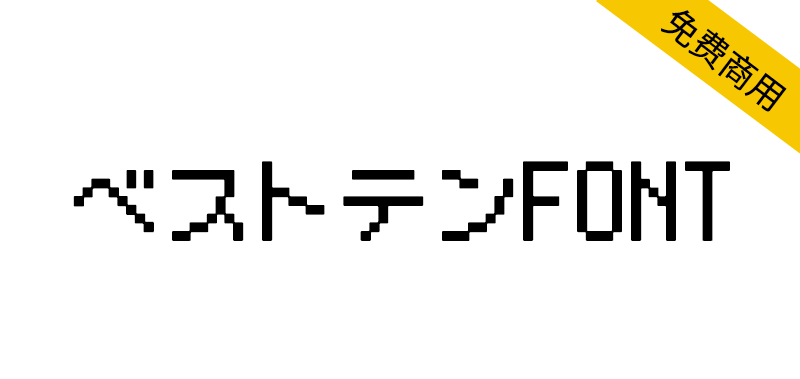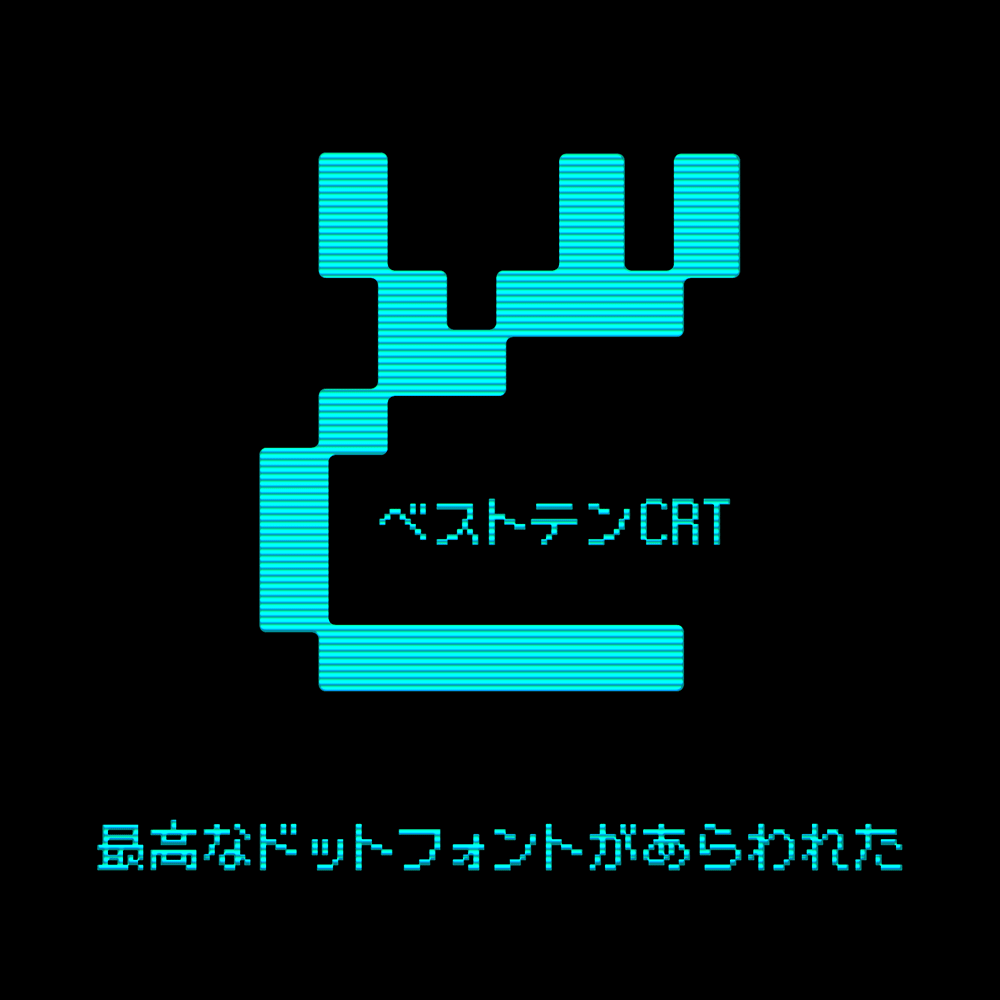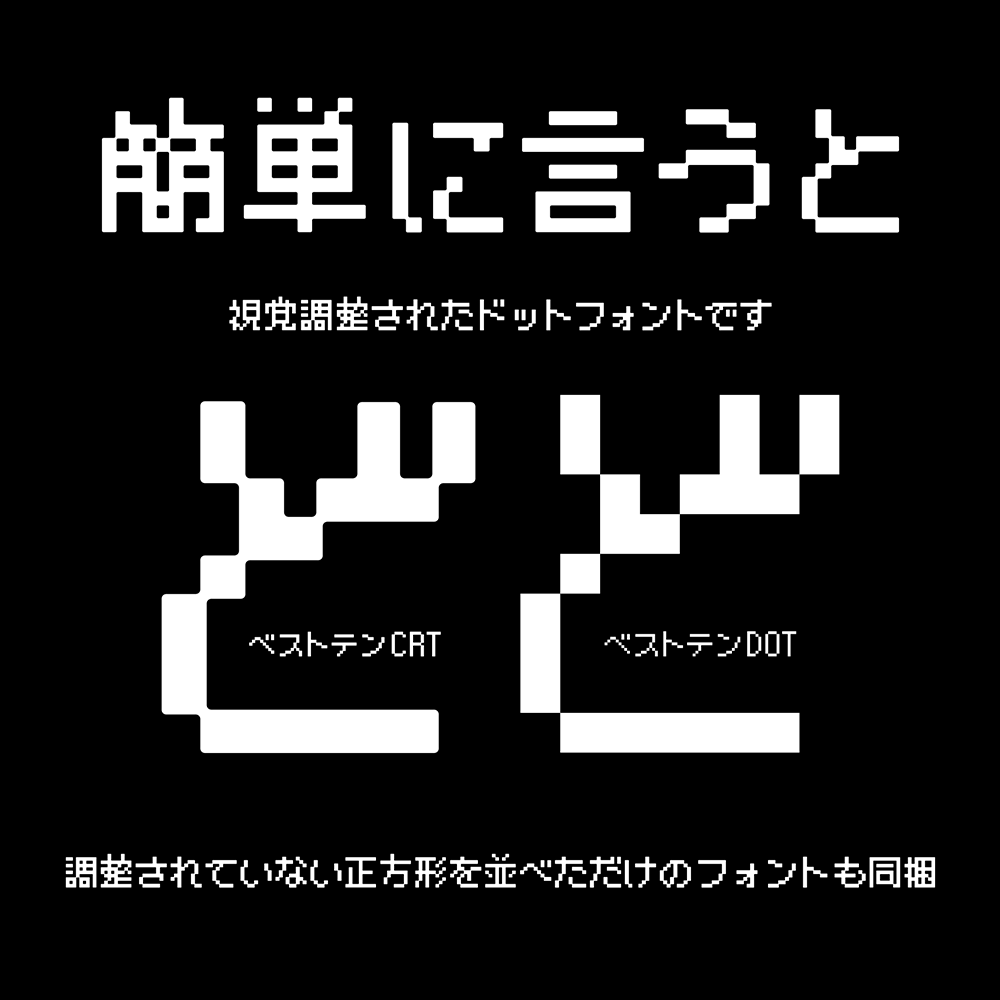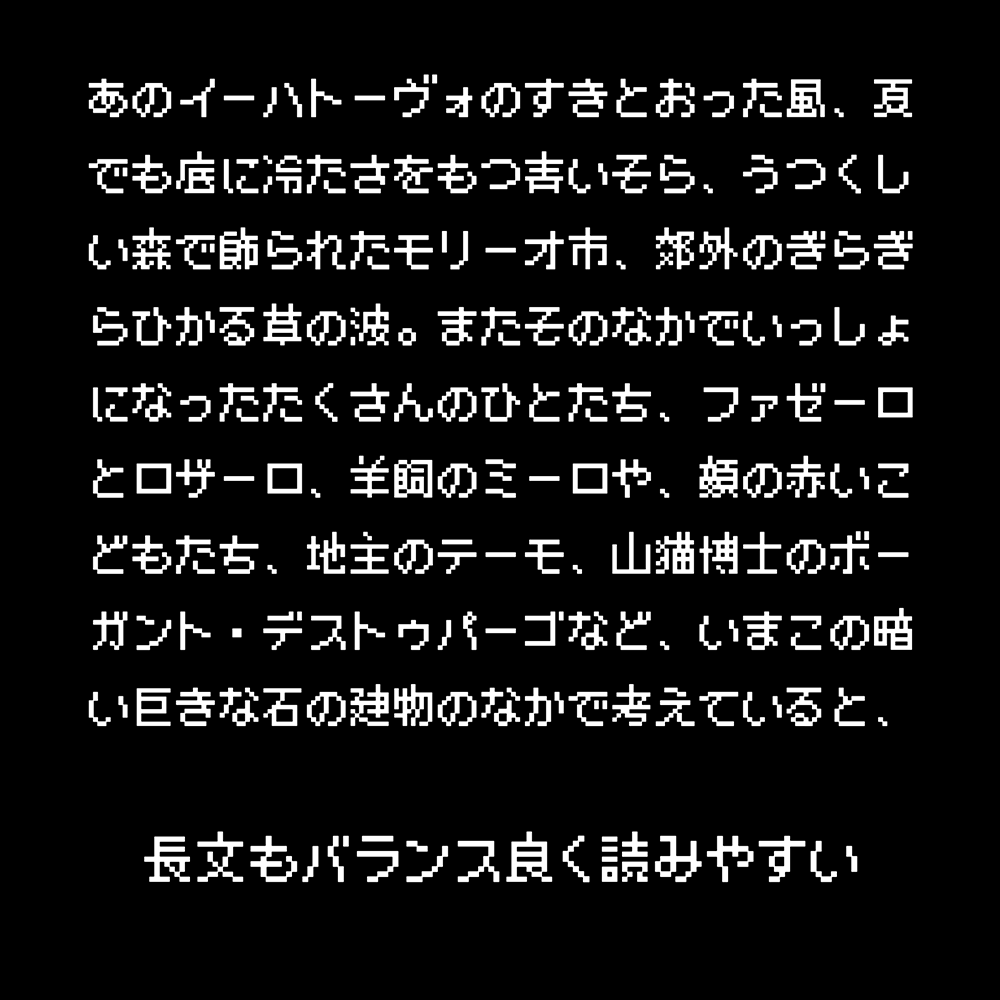
ベストテンFONT(BestTen),进行了视觉调整和加工的Best Ten CRT和只排列了点的Best Ten DOT两种。简单地说,这是一套只需直接使用就能像复古游戏和电脑一样的Best Ten CRT和纯粹作为点阵字体使用的Best Ten DOT。
原创制作了平假名、片假名、欧洲字符,剩下的部分用M+BITMAP FONTS的派生字体PixelMplus10补充。
10×10のドットフォント。視覚調整と加工のされたベストテンCRTと、ドットを並べただけのベストテンDOTの2種類。簡単に言うとそのまま使うだけでレトロなゲームやコンピューターっぽくなるベストテンCRTと、純粋にドットフォントとして使えるベストテンDOTのセットです。
ひらがな、カタカナ、欧文をオリジナルで制作し、残りの部分をM+ BITMAP FONTSの派生フォントPixelMplus10で補いました。